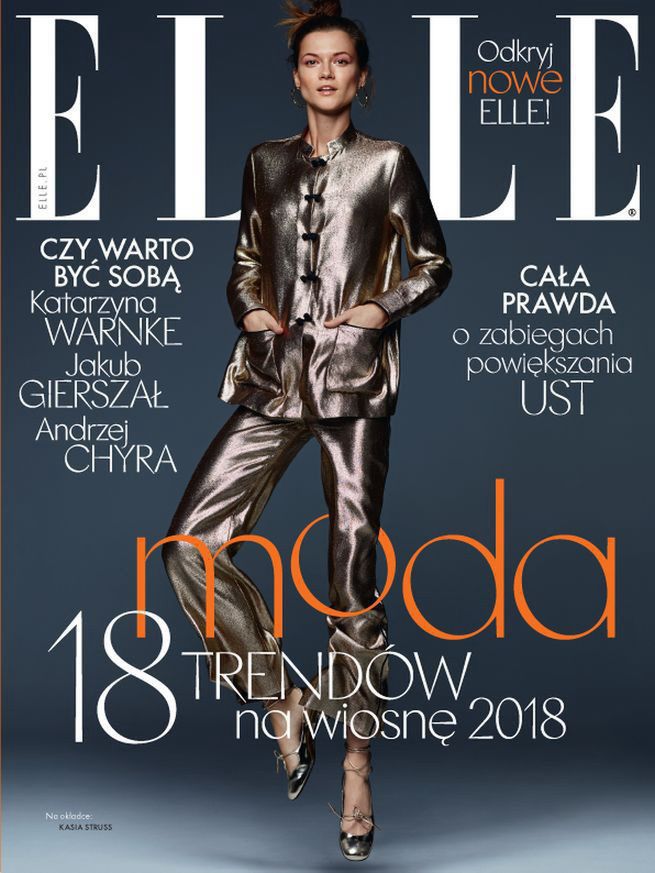
Zmiany w „Elle”: nowe działy, font, więcej o modzie i luksusie, hasło „Moja moda, moje Elle”
Marcowe wydanie miesięcznika „Elle” (Burda International Polska) ukazuje się w mocno odmienionej odsłonie: z odświeżoną szatą graficzną, nowymi rubrykami i zmienionym fontem. To pierwszy numer przygotowany przez nową redaktor naczelną Martę Drożdż. Metamorfozę przechodzi także serwis internetowy pisma.
Odmienione „Elle” ma także nowe hasło: „Moja moda, moje Elle”. Jak zapowiada redaktor naczelna, pismo stawia teraz na luksus, nowoczesność i modę. W marcowym wydaniu pojawiają się więc cztery sesje zdjęciowe, a tematy związane z modą zajmują 70 proc. numeru.
Prace nad relaunchem poprzedziły badania marketingowe. - Dzięki nim znamy dokładnie oczekiwania i preferencje naszych czytelniczek, wiemy, o jakim „Elle” marzą, i taki magazyn dla nich tworzymy. Nasze czytelniczki są aktywne, zaangażowane, orientują się w najnowszych trendach, czerpią z życia satysfakcję, codziennie poszukują nowych wrażeń, kochają modę i zakupy - mówi redaktor naczelna pisma, Marta Drożdż.
Zmiana wizualna magazynu jest gruntowna i obejmuje kilka elementów. - W makiecie wprowadziliśmy więcej światła, zmieniliśmy czcionkę na kobiecy font Play, który wyłącznie dla nas zaprojektowało londyńskie studio graficzne. Pismo ma teraz więcej świeżości, elegancji i luksusu - precyzuje szefowa „Elle”.
Zmienia się także struktura pisma. „Elle” ma teraz pięć głównych działów: „Trendy”, „Teraz”, „Uroda”, „Moda” i „Ekstra”. W rubryce „Trendy”, która skupia się na aktualnościach w modzie, wprowadzono stronę „Polska moda". Dzięki niej mają być odkrywani i promowani polscy projektanci.